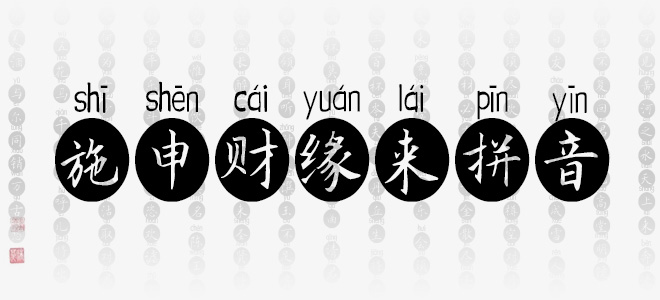
施申財(cái)緣來拼音是一款自帶中文拼音標(biāo)注效果的藝術(shù)字體,字體線條粗細(xì)適中,筆畫隨性,結(jié)構(gòu)灑脫自在,具有很好的視覺感,適合于文化類的宣傳設(shè)計(jì)、商業(yè)類品牌的廣告和產(chǎn)品包裝設(shè)計(jì)以及個(gè)性化文字排版等較多場景。
施申財(cái)緣來拼音